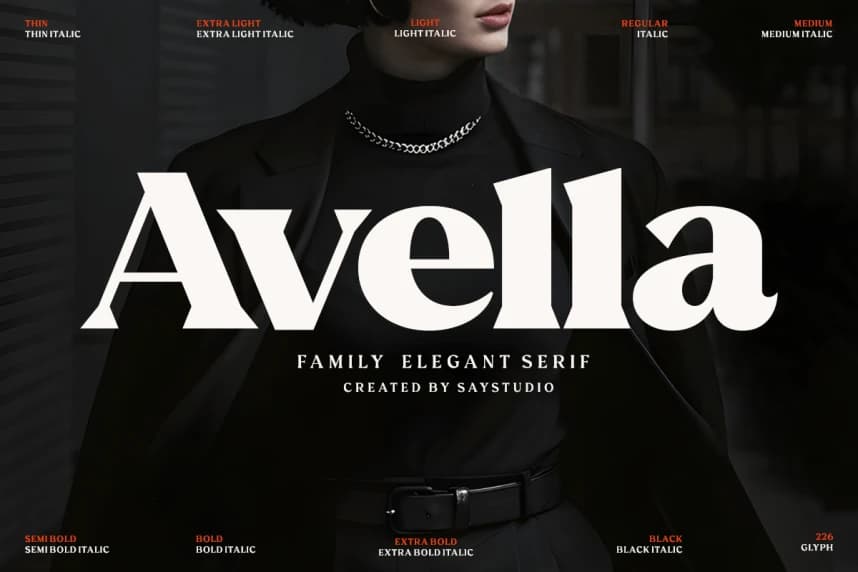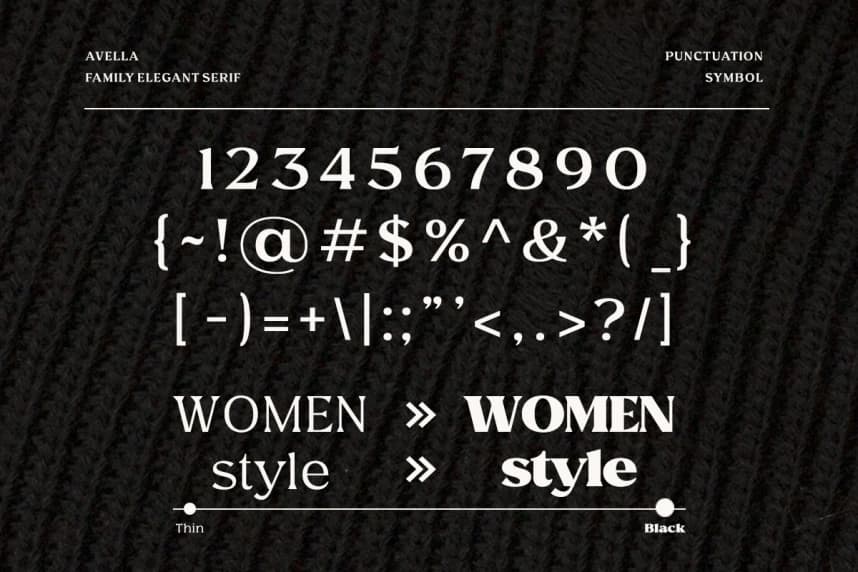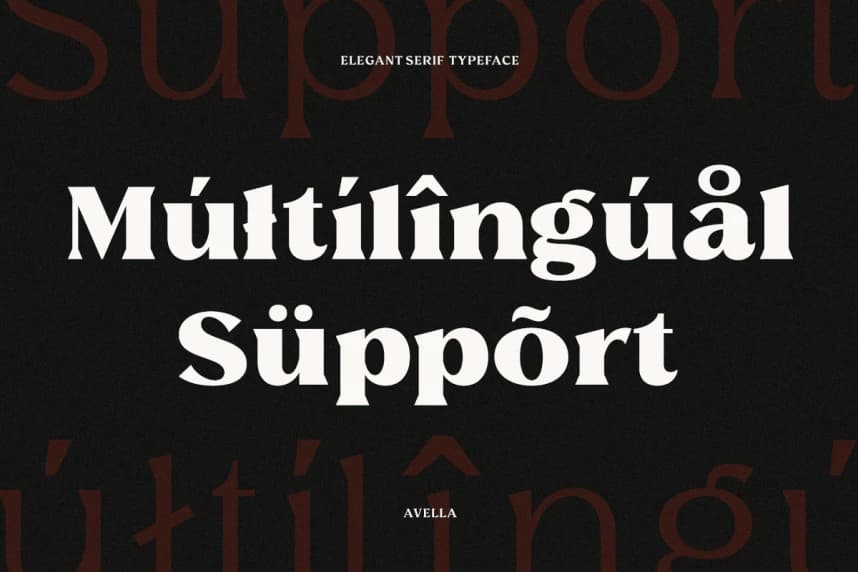
Avella Font
Avella Font, geniş bir yaratıcı uygulama yelpazesinde sofistike bir hava sunmak üzere tasarlanmış modern ve zarif bir serif font ailesidir. İnce yapısı ve yüksek kontrastlı hatlarıyla Avella, lüks ve profesyonelliğin özünü yakalıyor.
Avella Font, pek çok yaratıcı uygulama için zarafeti sunacak şekilde tasarlanmış modern ve zarif bir serif yazı tipi ailesidir. İnce yapısı ve yüksek kontrastlı hatlarıyla Avella, lüks ve profesyonellik özünü yakalar.
Avella
Avella Regular